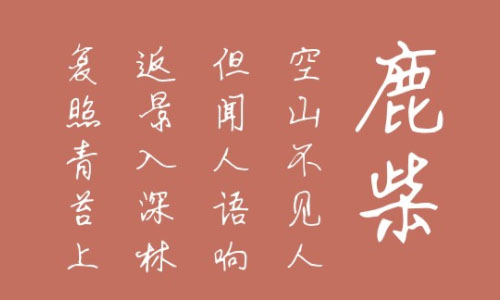
倉(cāng)耳夢(mèng)醒的離別體字體是一款很漂亮的硬筆手寫(xiě)藝術(shù)字體,該字體風(fēng)格飄灑自然,運(yùn)筆蒼勁有力,一氣呵成,最大限度的還原日常書(shū)寫(xiě)的字體風(fēng)格,更加自然 ,舒適,設(shè)計(jì)師最大限度的將日常書(shū)寫(xiě)的風(fēng)格帶入字體,使字體筆走龍蛇,瀟灑自然。歡迎大家前來(lái)下載。